בעולם שבו הכול דיגיטלי והתחרות נמצאת בכל פינה, פונטים בעברית לשימוש מסחרי הם הרבה יותר מסתם "כתב יפה". הם יכולים לשמש ככלי שיווקי חזק, שמספק למותג זיהוי חזותי ברור ומושך, המעביר את ערכיו ומסריו בצורה האפקטיבית ביותר.
פונט נכון יכול להבדיל את המותג שלך מהמתחרים ולהעלות אותו לטופ. בואו נדבר על איך לבחור את הנשק הסודי הזה: רישיון השימוש בפונט, הייחודיות שהוא מביא עמו והאסתטיקה שתדבר בשפת הלקוח ותשדר את תחושותיו וערכיו.הבחירה בפונט המתאים דורשת הבנה של המותג והשוק, כמו גם התחשבות בטרנדים העכשוויים בעיצוב. פונטים איכותיים יכולים לשדר מקצועיות ולסייע ביצירת קשר רגשי עם הלקוחות, דבר הכרחי להצלחת כל מותג.
כשמדובר בעסקים, התחושה שמותג משדר משפיעה מאוד על תדמית העסק. פונטים בעברית באיכות גבוהה מעבירים רמת רצינות ומקצועיות שפונטים חינמיים לפעמים פשוט לא יכולים להתמודד איתה.
שימוש בפונטים בעברית לשימוש מסחרי גם מבטיח שהמותג שלך יהיה ייחודי. פונטים חינמיים בדרך כלל נשחקים מהר יותר ומאבדים מהייחודיות. לכן, השקעה בפונט מורשה ומקורי מסייעת לשמר את תחושת הבלעדיות והמקצועיות של המותג, תוך שימוש באלמנטים טיפוגרפיים שלא נמצאים בשימוש נרחב.
פונטים בעברית לשימוש מסחרי לא רק שנראים טוב יותר, הם גם מגיעים עם תמיכה שלא תמצאו באף פונט חינמי.
החיסרון עם פונטים חינמיים היא שלעיתים הם מגבילים אותך לגבי השימושים, ולעיתים האיכות שלהם מוטלת בספק.
כשמחפשים פונטים בעברית לשימוש מסחרי, חשוב להתחשב בפקטורים כמו קריאות, אסתטיקה, והתאמה לזהות המותג. מומלץ לבחור פונט שישרת את המסר שהעסק שלך מנסה להעביר.
למשל עסק עממי שרוצה לשדר חמימות ואותנטיות יבחר פונט כתב יד, ועסק שרוצה לפנות לקהל יעד מתוחכם וטכני יבחר בפונטים סנס סריפיים ומודרניים.
לפעמים, שימוש בפונט טרנדי יכול לתרום הרבה למותג. פונט כזה יכול להציג חדשנות ולמשוך קהל צעיר יותר. עם זאת, חשוב לזכור שטרנדים משתנים, ופונט שהוא פופולרי היום יכול להפוך למיושן מחר. שימוש בפונט טרנדי יכול לעזור להבליט את המותג ולהציג אותו כחדשני ועכשווי. פונט טרנדי יכול להיות יעיל במיוחד בקמפיינים פרסומיים ושיווקיים.
הוא מאפשר למותג לבלוט בקרב קהל היעד שלו בצורה חזקה . זה יכול להיות פונט עם עיצוב ייחודי שמשדר חדשנות, כמו למשל פונט בננה או פונטים מסורתיים יותר שמתאימים לעיצובים בעלי רקע דתי או רשמי. השימוש בפונטים מיוחדים מאפשר לעסק להבדיל את עצמו מהמתחרים ולהקנות ללקוחות תחושה של ייחודיות ואקסקלוסיביות.
חשוב לציין שהשימוש בפונטים מיוחדים בעברית אינו רק עניין של טרנד אלא גם של אסטרטגיה שיווקית מושכלת. פונט מתאים יכול להפוך חומר שיווקי למושך יותר ומעניין יותר, ולכן כדאי להשקיע זמן ומחשבה בבחירת פונטים בעברית לשימוש מסחרי המושלמים לצרכים לשכם.
הייתי ממליצה לשלב בספריית הפונטים שלכם פונטים קלאסיים שיתאימו לכל פרויקט יחד עם פונטים ייחודים לכותרות או חומרים פרסומיים.
בחירה בפונטים בעברית לשימוש מסחרי היא תהליך שחייב להתבצע בזהירות ובמקצועיות. פונט שמתאים לצרכים
שלנו יכול להוביל לשיפור בתדמית העסקית ולקידום מכירות. אל תפחדו להשקיע בפונט איכותי שישדרג את התקשורת שלכם עם הלקוחות ויציב אתכם כשחקנים מובילים בשוק.
הפונט המתאים משדר איכות ומקצועיות, משפר חוויות משתמש, ומקדם מכירות על ידי הגברת התעניינות והקלה על קריאה והבנה של המידע המוצג. בין אם מדובר בלוגו, בממשק משתמש, או בחומרי שיווק ופרסום, פונט מותאם ומיוחד יכול להוביל להבדל המהותי באיך שהלקוחות והקהל הרחב תופסים את המותג. לכן, חשוב לא להתפשר על האיכות ולבחור בפונט שמתאים בדיוק לצרכים האישיים והמקצועיים של העסק.
בנוסף, רישיונות עשויים להגביל את מספר המשתמשים או המכשירים שיכולים להשתמש בפונט, דבר שמחייב תשומת לב מיוחדת בעת הקנייה לשימוש עסקי גדול-היקף.
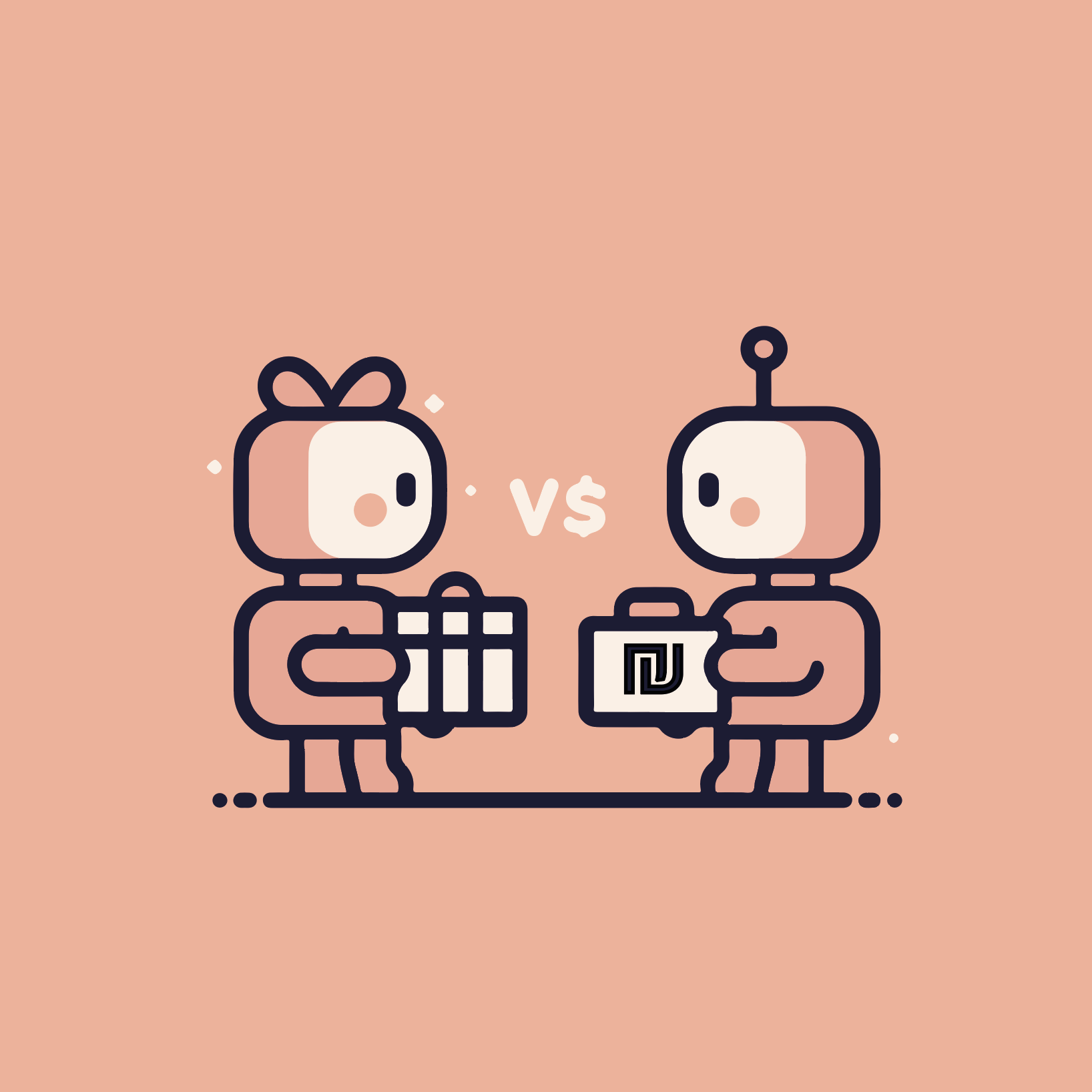
כן, קיימים פונטים שנועדו במיוחד לשימוש בדפוס המספקים תוצאות טובות יותר על גבי נייר, ופונטים אחרים שמותאמים למסכים, אשר מעוצבים להצגה ברורה יותר בתאורה משתנה ורזולוציות שונות. חשוב לבחור את הפונט המתאים למדיום שבו התוכן יוצג.
פונטים דינמיים הם פונטים שניתן לשנות את תכונותיהם בזמן אמת, כגון עובי, רוחב או סגנון. הם מאפשרים גמישות רבה בעיצוב ובהתאמה לצרכים שונים, ויכולים להיות מועילים במיוחד בפרויקטים דינמיים כמו אתרים אינטראקטיביים או אפליקציות.